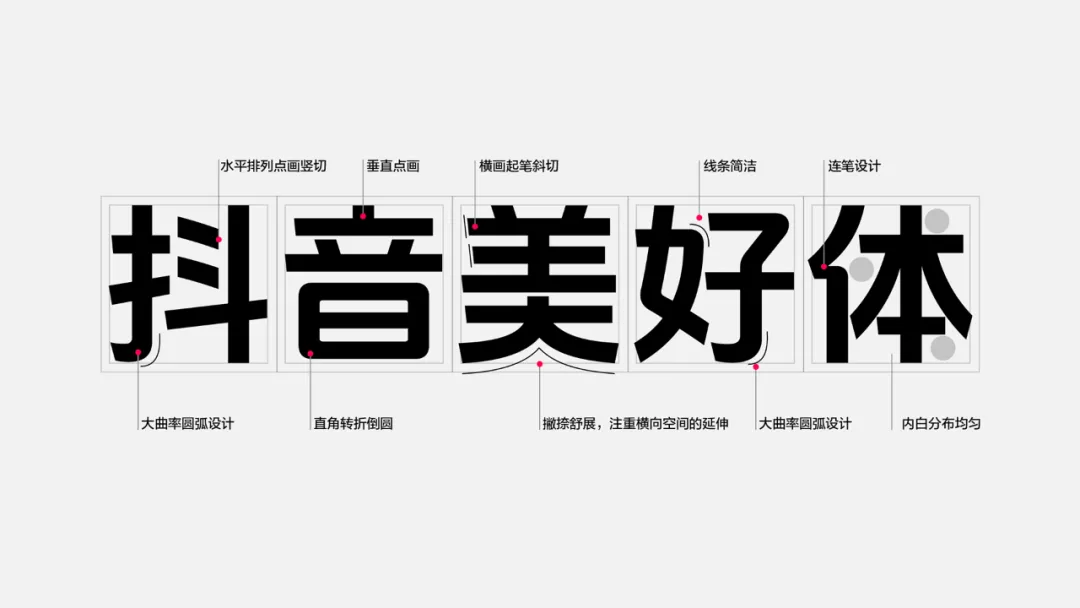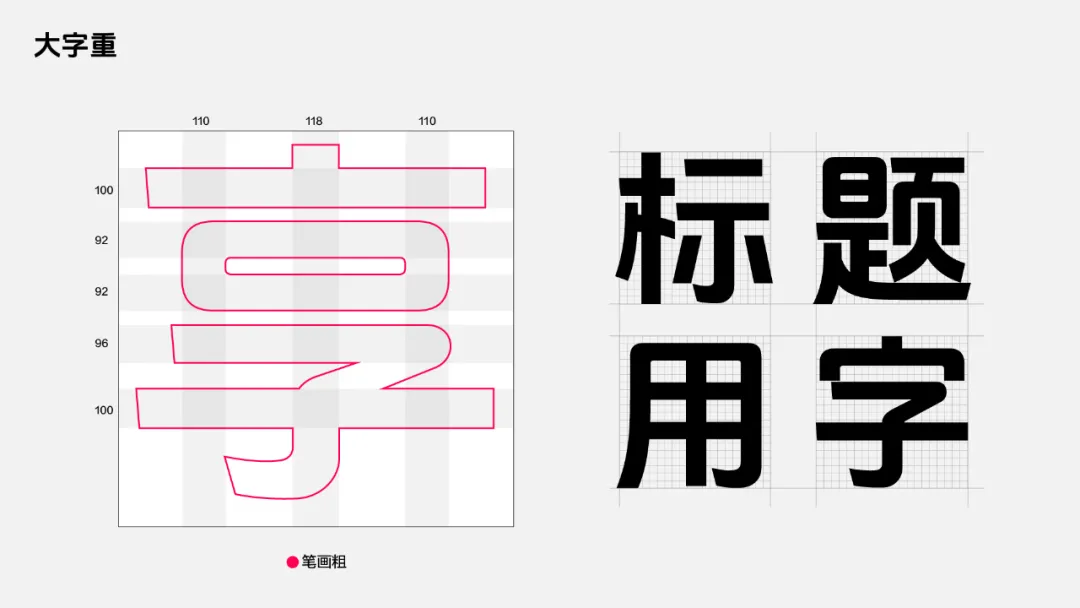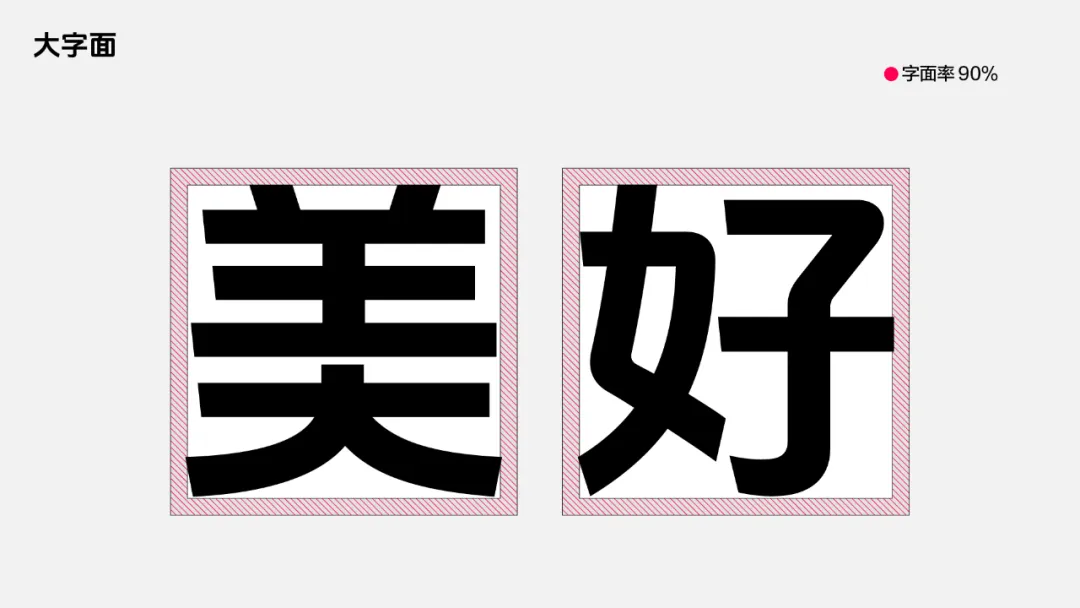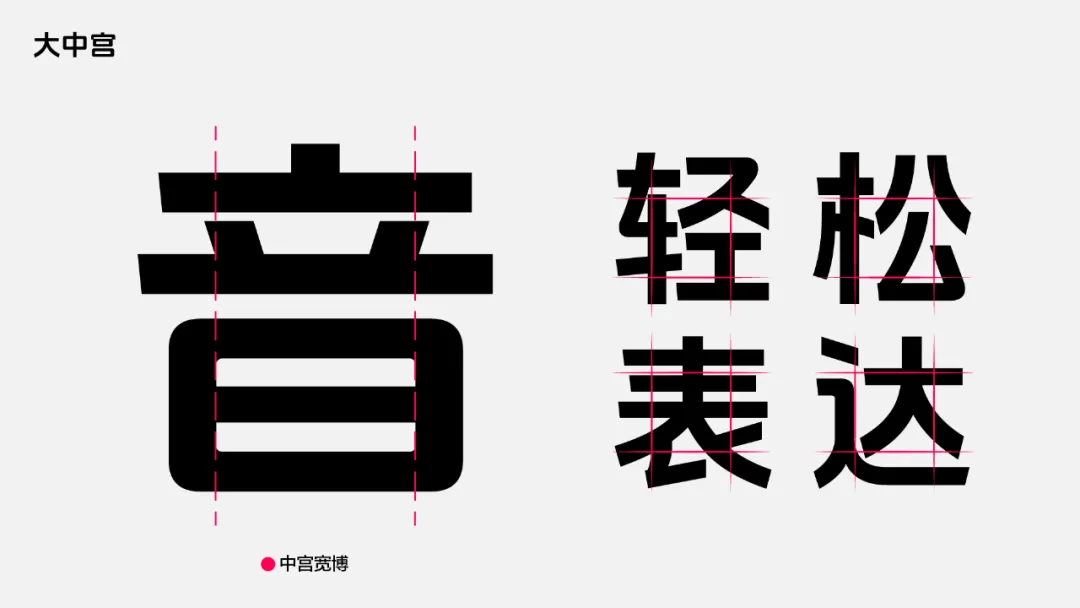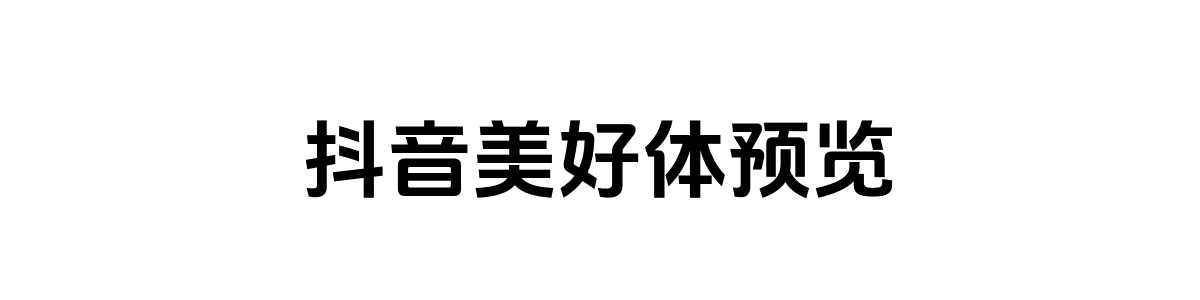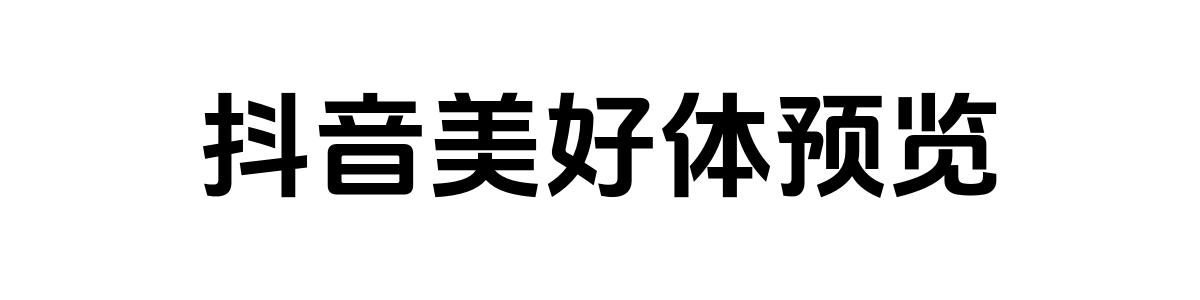
抖音美好体
抖音美好体(Douyin Sans Bold)是抖音体验设计中心与方正字库联合打造并于2023年开源发布的一款品牌定制字体。作为”记录美好生活”品牌理念的视觉载体,这款字体以现代简洁的笔形、饱满舒展的结构,完美平衡了标题的视觉张力与屏幕阅读的舒适性。
字体严格遵循 GB2312 标准,包含6763个中文字符及682个西文字符。其特有的高字面率设计与统一中宫结构,能够在各类数字场景中都能保持清晰易读的显示效果。
字体风格
抖音美好体的设计精髓体现在现代几何结构与人文细节的完美融合。笔形采用独创的圆弧化处理,弯钩笔画运用大曲率圆弧展现流畅韵律,折笔处通过内直外弧的倒角设计形成独特的”刚柔并济”视觉效果。横笔末端的斜切处理源自书法”露锋”笔意,为规整的字体注入灵动笔触。